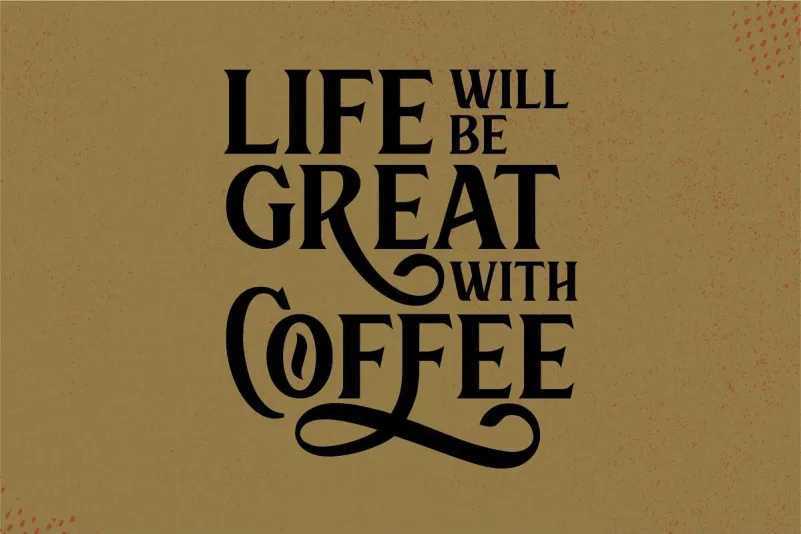
Aproveite para dar um toque sofisticado e elegante à sua identidade visual com a Sultan Serif Font, uma tipografia serif bold que oferece alternativas criativas e ligaturas perfeitas para criar ricos logotipos de marca personalizada ou empresarial. Esta fonte apresenta um formato vintage, reforçado com elementos decorativos modernos e formas minimalistas, tornando-a ideal tanto para criações gráficas como para aplicações em projetos digitais. Aproveite o suporte multilíngue dessa fonte, que permite uma vasta gama de usos, incluindo logotipos, marcas de marca, desenhos de protótipos e diversos outros projetos. Perfeita para quem está em busca do formato vintage elegante, a Sultan Serif Font é um recurso gráfico imprescindível para qualquer designer que busca criar uma identidade visual única e sofisticada.